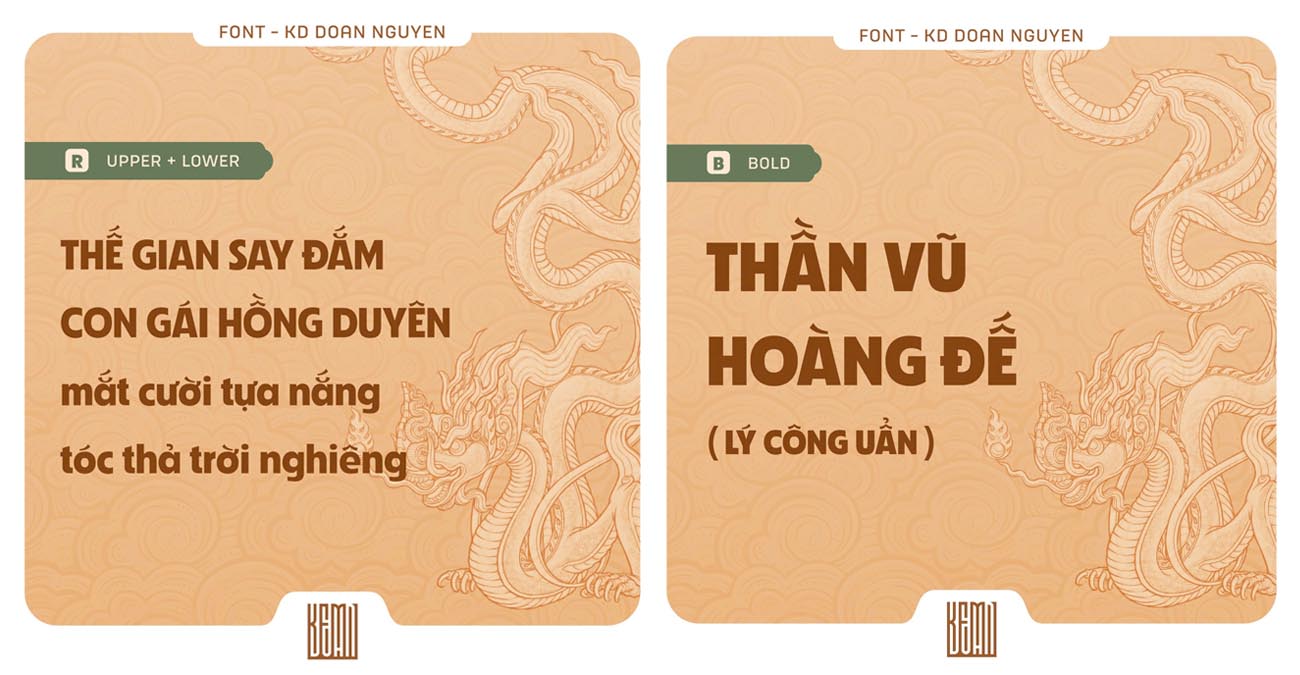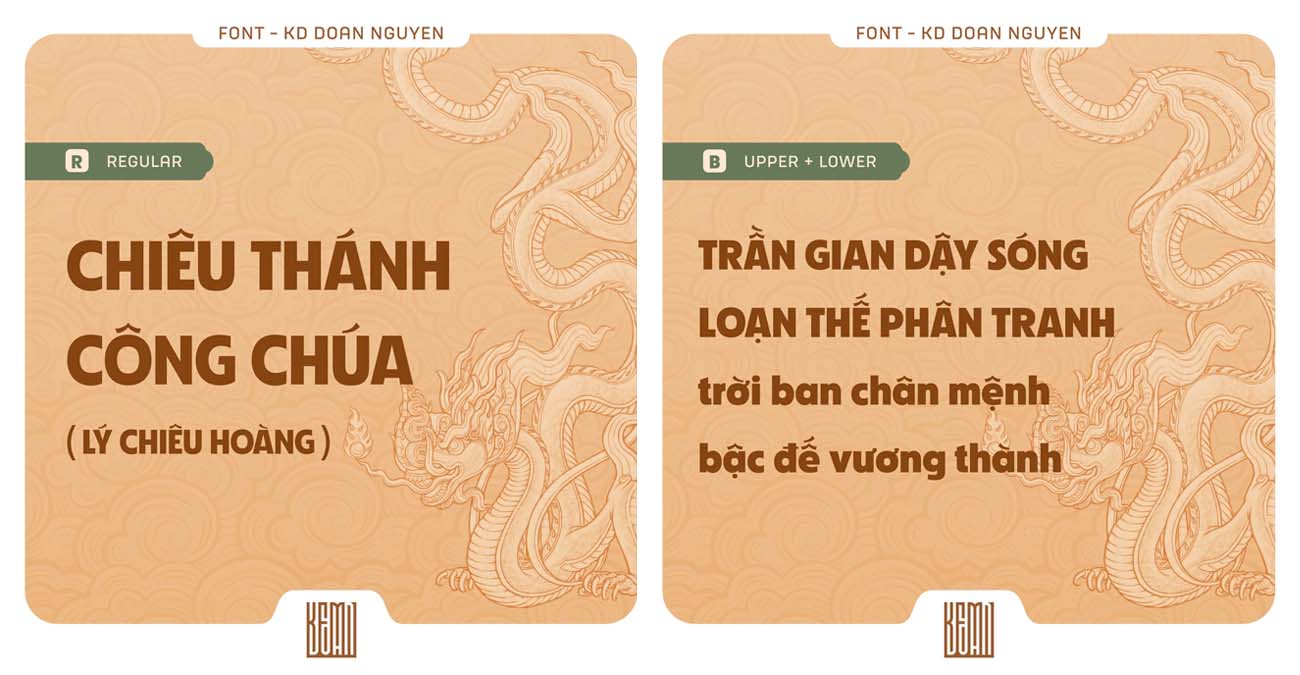
Tải Font KD Doan Nguyen – Font Việt Hóa Mang Dấu Ấn Lịch Sử
Font chữ KD Doan Nguyen là một kiểu font lịch sử mang phong cách trang trọng, mạnh mẽ và gợi nhớ tinh thần hào hùng của dân tộc. Các đường nét của font được thiết kế dày dặn, chắc chắn, góc cạnh rõ ràng, tạo cảm giác vững chãi và quyền lực – rất phù hợp để tái hiện khí thế các triều đại xưa.
Điểm đặc biệt của KD Doan Nguyen là khả năng cân bằng giữa tính hiện đại và nét cổ điển. Bộ font đã được Việt hóa hoàn chỉnh, hỗ trợ đầy đủ tiếng Việt, giúp dễ dàng sử dụng trong các ấn phẩm thiết kế như poster, bìa sách lịch sử, banner sự kiện, hay các dự án sáng tạo lấy cảm hứng từ văn hóa truyền thống.
Với sự kết hợp giữa giá trị thẩm mỹ và tính ứng dụng, KD Doan Nguyen trở thành lựa chọn lý tưởng cho những nhà thiết kế muốn truyền tải tinh thần lịch sử, lòng tự hào dân tộc và sự trang nghiêm trong từng tác phẩm.